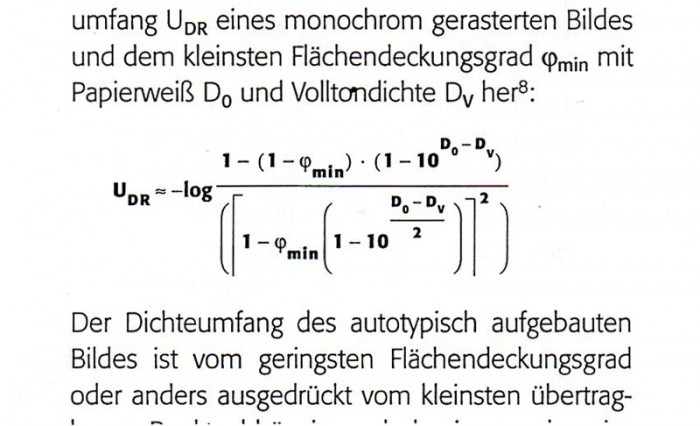
Guten Morgen!
Diese Formel hier stammt aus der Dissertation von Gerhard Fischer und beschreibt den Zusammenhang zwischen Dichteumfang und Flächendeckung beim frequenzmodulierten Raster.
Ich hatte sie 1994 mit FrameMaker aufgebaut, was einfach und schnell gelang. Bis auf die fehlenden unteren Abschlüsse bei den eckigen Klammern sieht sie ganz passabel aus, finde ich,
Wie würdet Ihr eine solche Aufgabe heutzutage lösen? Mit Word? LaTeX? Mathematica? InDesign?
Formeln in diesem Stil sind natürlich krass ...!
Ab und zu habe ich für technische Beschreibungen solch umfangreiche Formeln auch zu setzen. Da aber die Agentur, für diese ich das mache, Indesign-Dokumente verlangt, habe ich noch nie ernsthaft über Alternativen nachgedacht (und ausprobiert).
Machbar ist das schon mit Indesign, ist halt ein wenig umständlich, da man oft nicht um mehrere, ineinander verschachtelte Textrahmen herumkommt. Ich habe mir einen Master erzeugt, mit mitwachsenden Textrahmen, alles als Gruppe im Fließtext verankert. Bei einfacheren Formeln kommt man evtl. um ein "Gruppe-im-Fließtext-verankern" herum, bei derart vielen Objekten nicht. (Soweit mein Stand).
Aber vielleicht gibt es ja ganz andere Alternativen mit anderen Programmen ...?
Doch wenn die Formeln wie in deinem Beispiel im Text mitlaufen (sollen), müsstest du ja diese Dateien aus einem anderen Programm verlinken und bei Korrekturwünschen jedes Mal extern bearbeiten.
Mit LaTeX könnte das Ergebnis so aussehen:
Der Code für die Formel lautet:
\begin{displaymath}
U_{DR} \approx -\log \frac{%Zähler
1 - ( 1 - \varphi_{\min}) \cdot (1 - 10^{D_0-D_V})
}{%Nenner
\left(
\left[
1 - \varphi_{\min}
\left(
1 - 10^{\frac{D_0-D_V}{2}}
\right)
\right]^2
\right)
}
\end{displaymath}
Na, das habe ich schon geahnt, dass LaTeX hier ein wirklich gutes Ergebnis bringen würde. Vielen Dank. Wie lange hast Du denn gebraucht? Und: Hat LaTeX einen grafischen Formeleditor wie früher FraneMaker?
Nun, das ist ja gerade der Witz, oder der Knackpunkt, je nachdem, wie man es sieht in dem ganzen TeX-Universum, dass es hier eben kein WYSIWYG gibt, sondern dem internen digitalen Setzer quasi den Satz erklärt, als würde man den einem realen Setzer per Telefon übermitteln, und darauf folgt dann WYGIWYW* - also: Du bekommst von dem Programm geliefert, was du durch die Erklärung, die du dem Programm gegeben hast, gewünscht hast. Man muss die Formel also letztlich so verfassen, wie man sie jemanden vorlesen würde, SDas Programm sorgt sich dann um die richtige Größe und Platzierung der mathematischen Zeichen.
*) WYGIWYW = What You Get Is What You Want
Bei der Formel frage ich mich allerdings, ob die äußere, runde Klammer im Nenner überhaupt erforderlich ist und
\begin{displaymath}
U_{DR} \approx -\log \frac{%Zähler
1 - ( 1 - \varphi_{\min}) \cdot (1 - 10^{D_0-D_V})
}{%Nenner
\left(
1 - \varphi_{\min}
\left[
1 - 10^{\frac{D_0-D_V}{2}}
\right]
\right)^2
}
\end{displaymath}
nicht eine identische Aussage hätte.
Wie catfonts schon sagte: den Formeleditor braucht man gar nicht, da man die Struktur der Formel eingibt und nicht das Layout. Ein Glück, denn als Nicht-Fachmann hätte ich das nie hinbekommen. LaTeX übernimmt das alles für mich.
Für die Formel selbst habe ich fünf Minuten gebraucht. Weitere fünf Minuten, um die Schrift umzustellen.